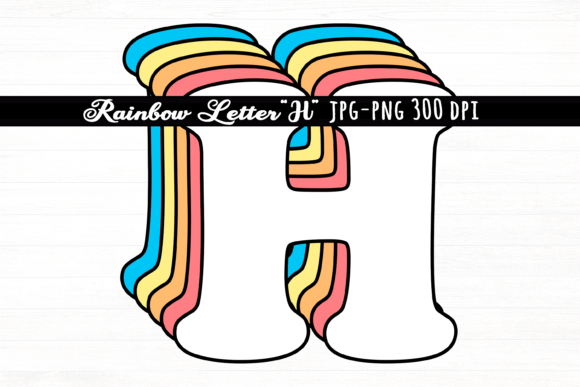
Letter H Rainbow Initial Cute Retro Font
Jika Anda mencari aset berkualitas tinggi seperti Letter H Rainbow Initial Cute Retro Font, paket premium ini adalah pilihan fantastis untuk proyek kreatif Anda.
Baik Anda membuat produk POD (Print on Demand), undangan pernikahan, atau grafis media sosial, Letter H Rainbow Initial Cute Retro Font adalah pilihan yang sangat ideal.